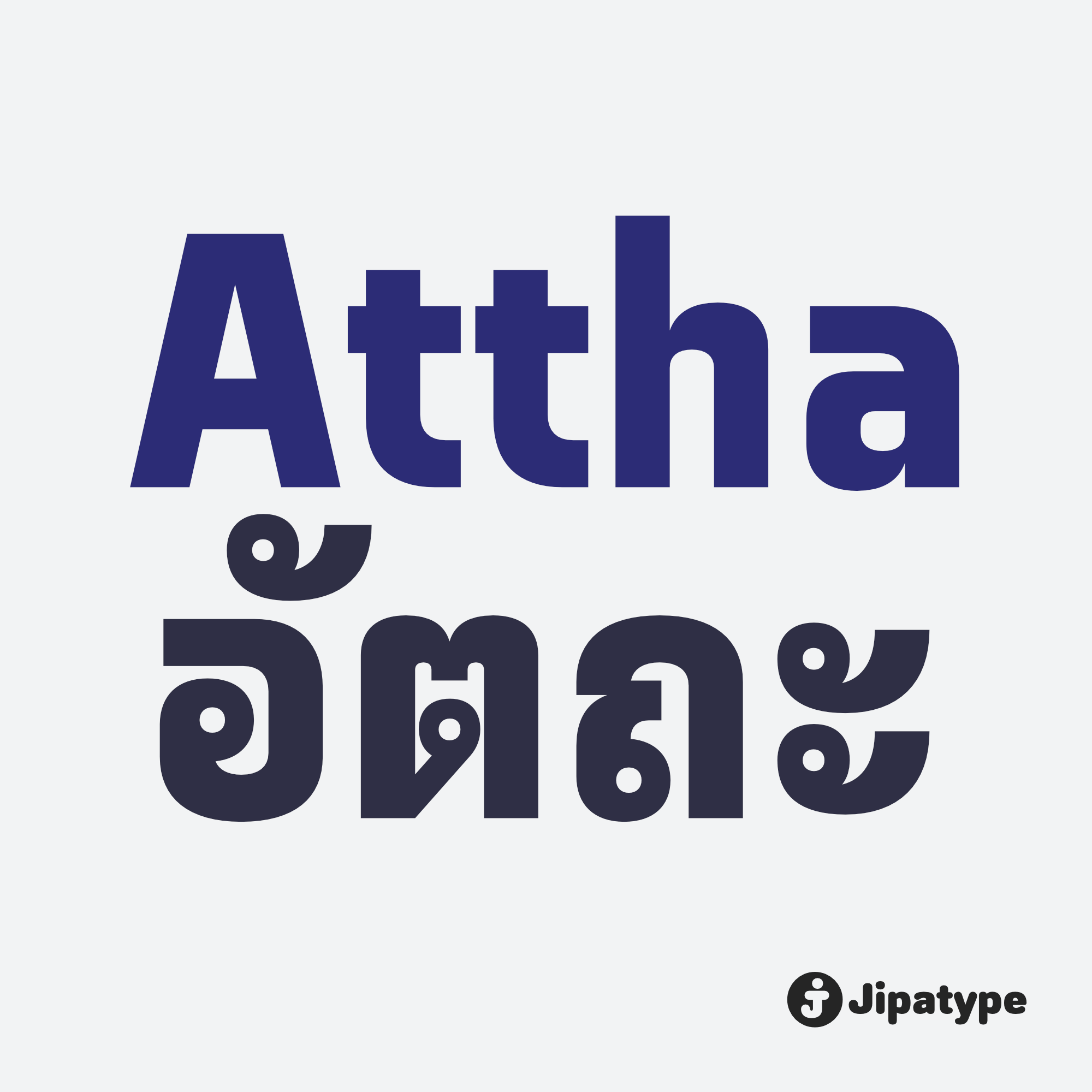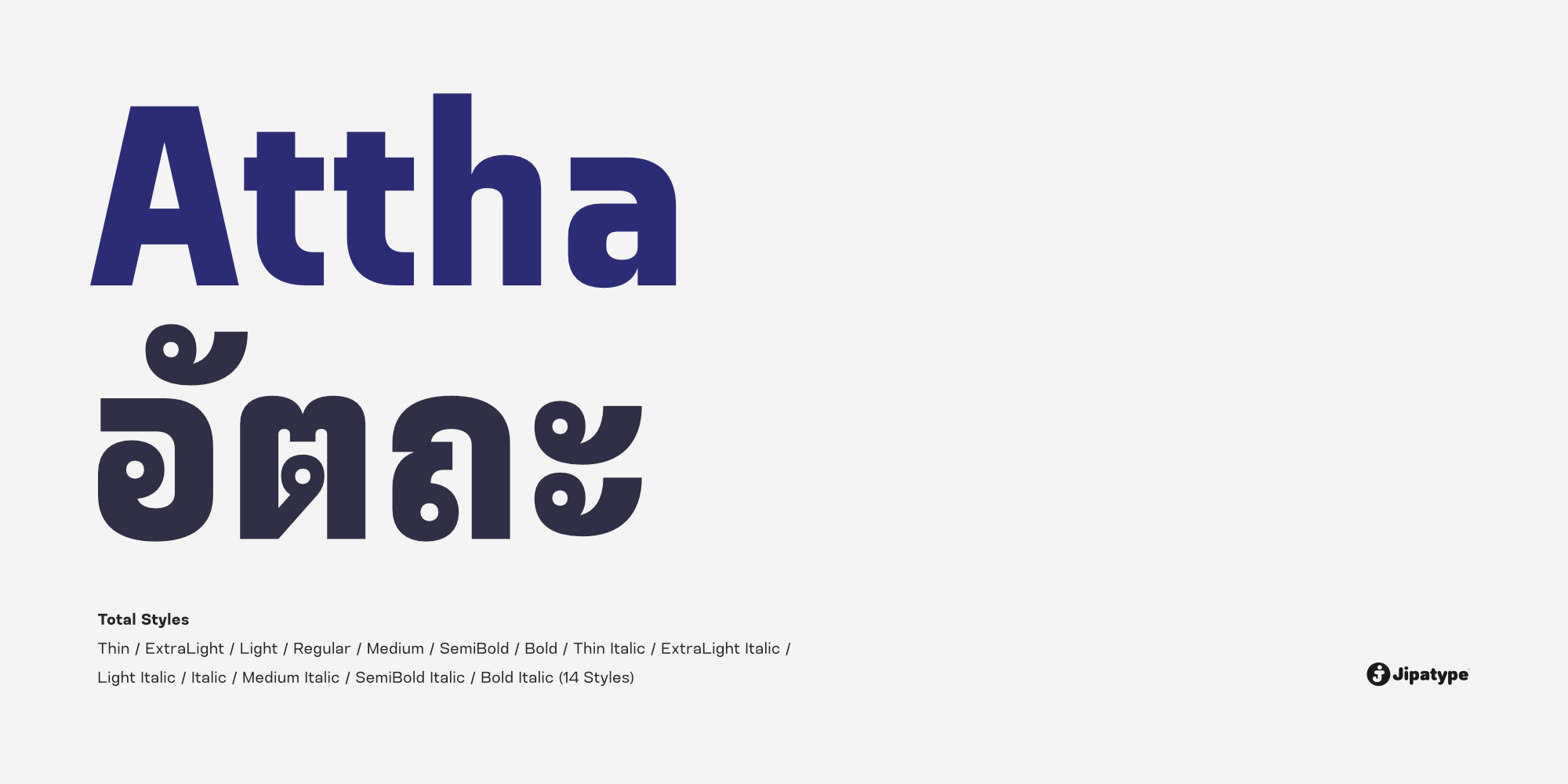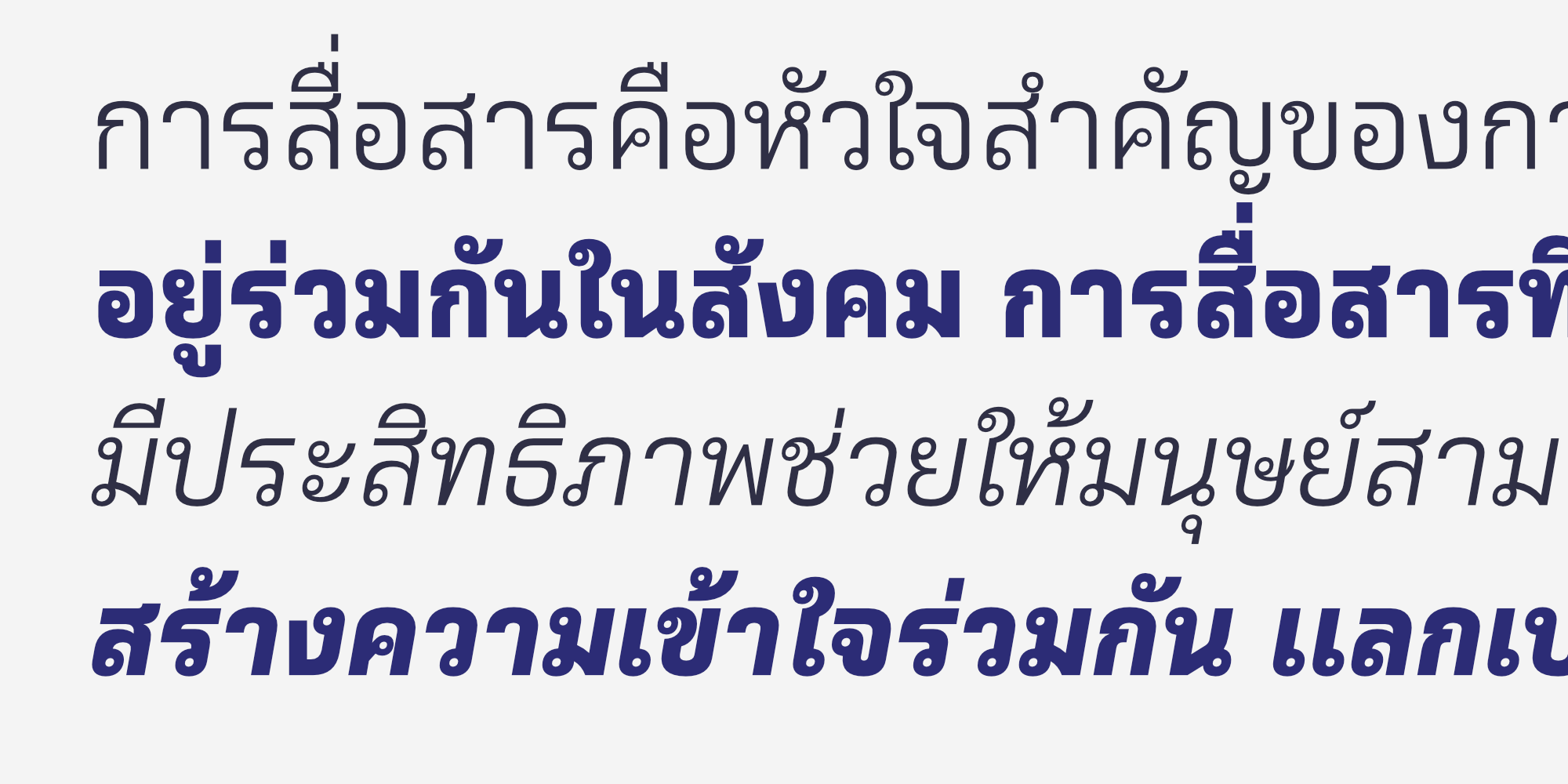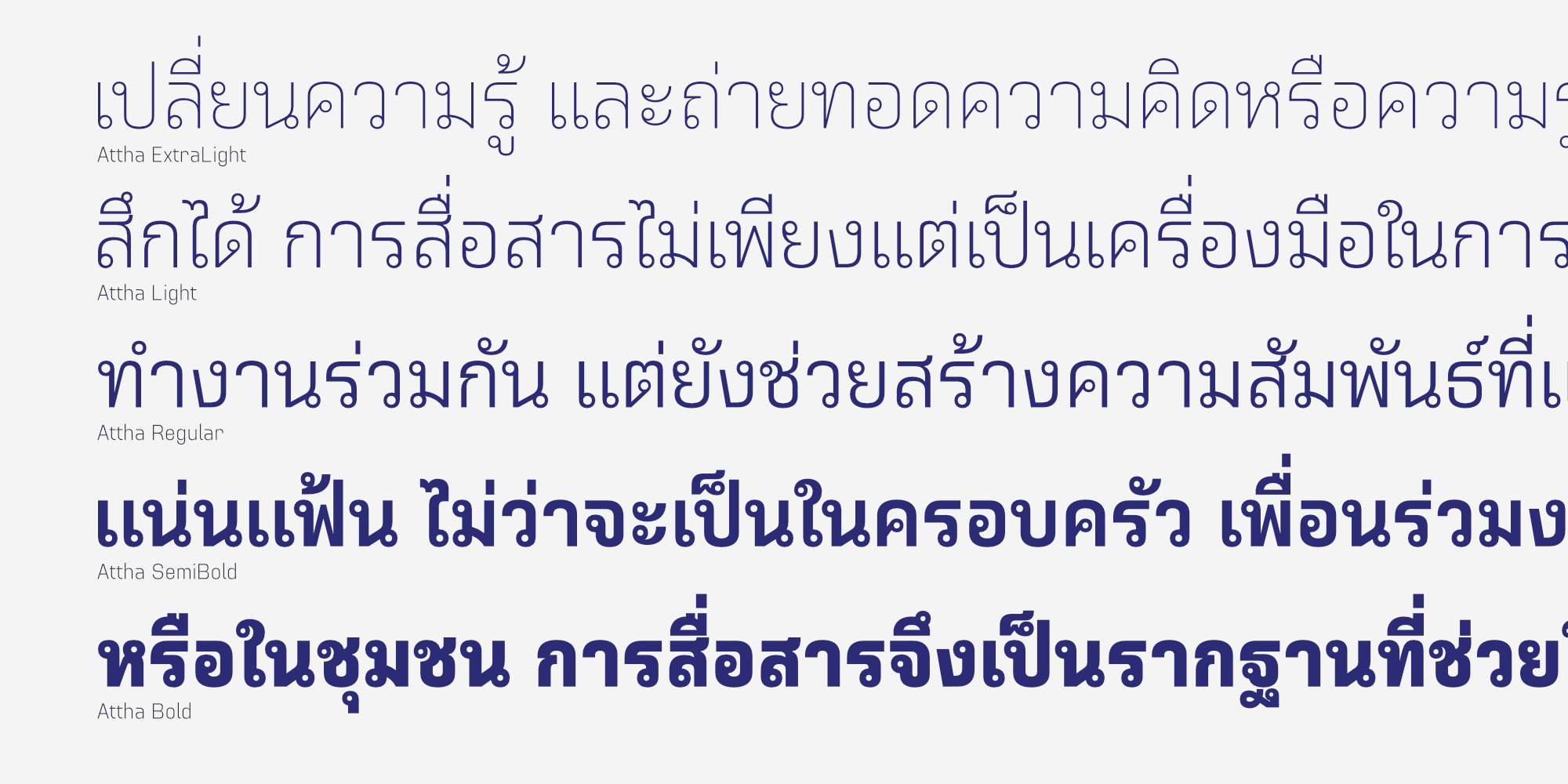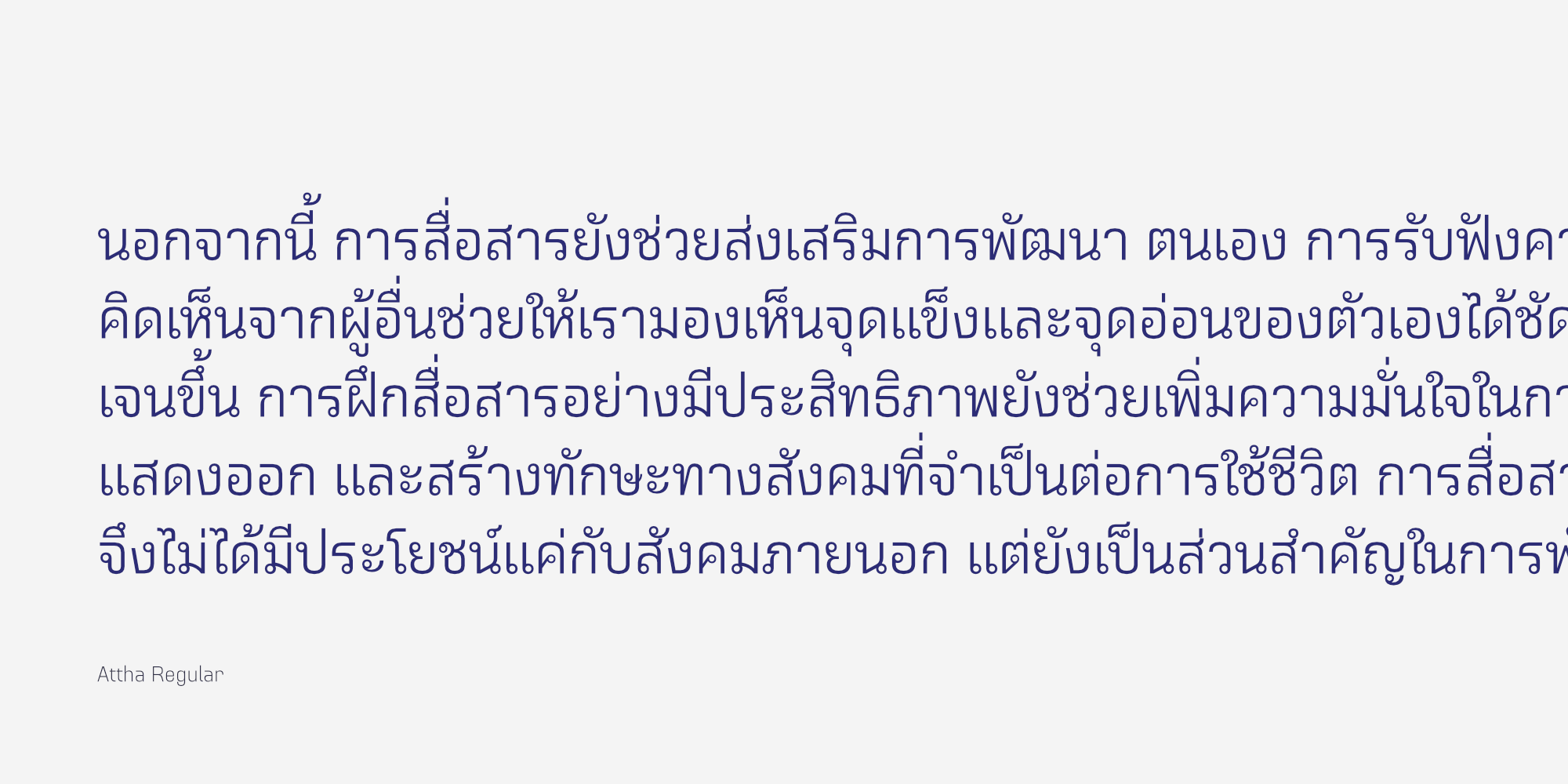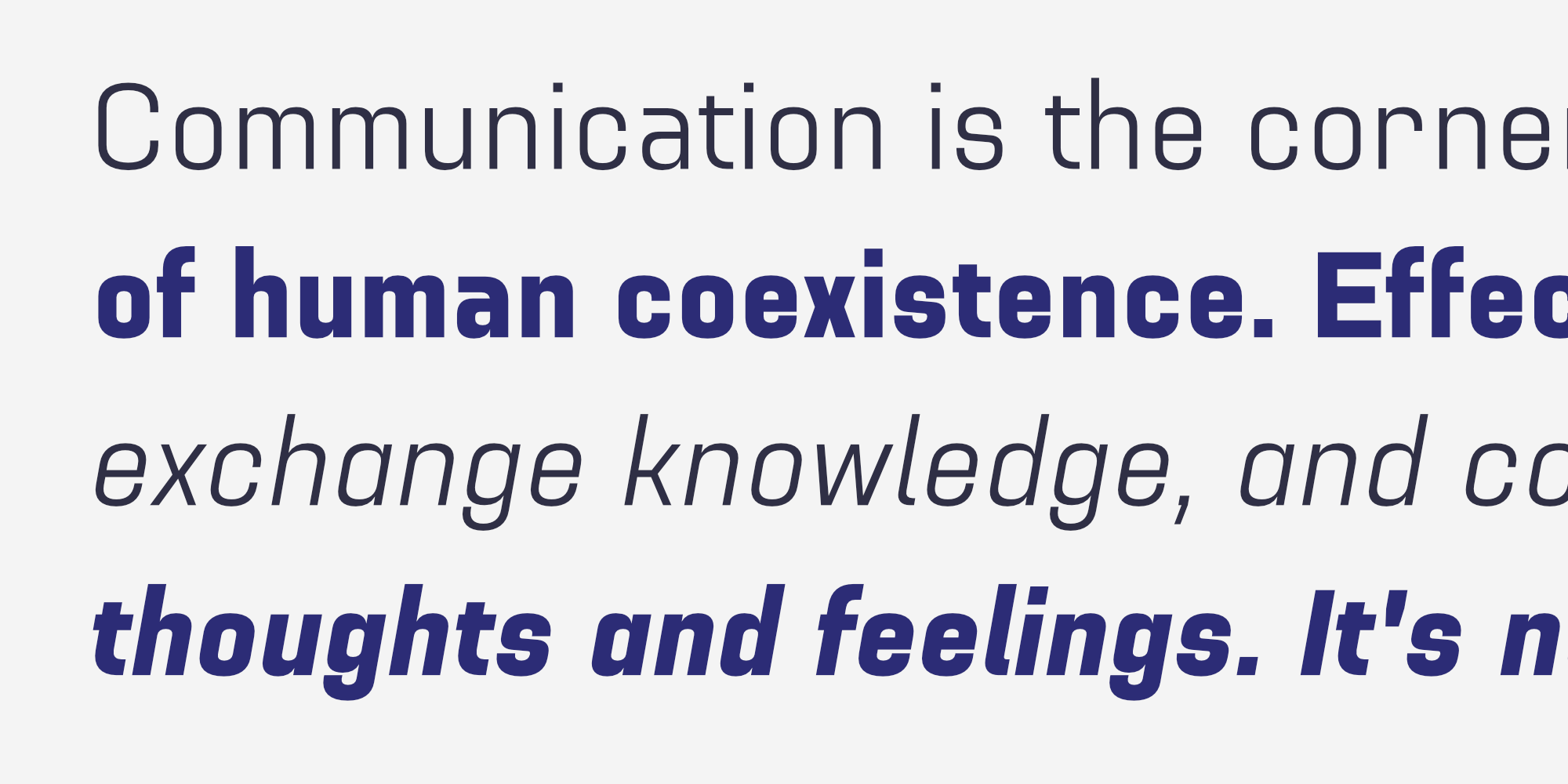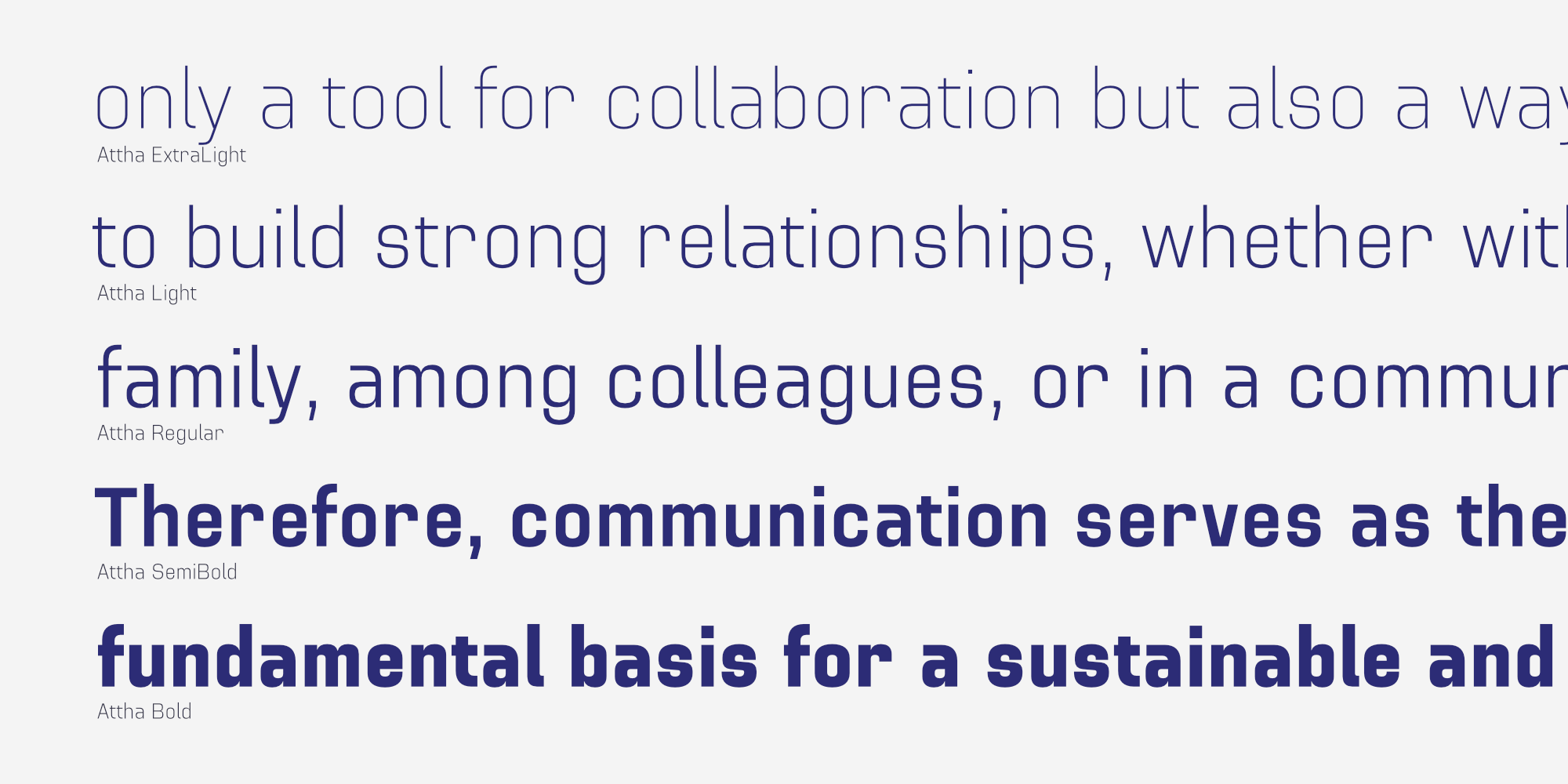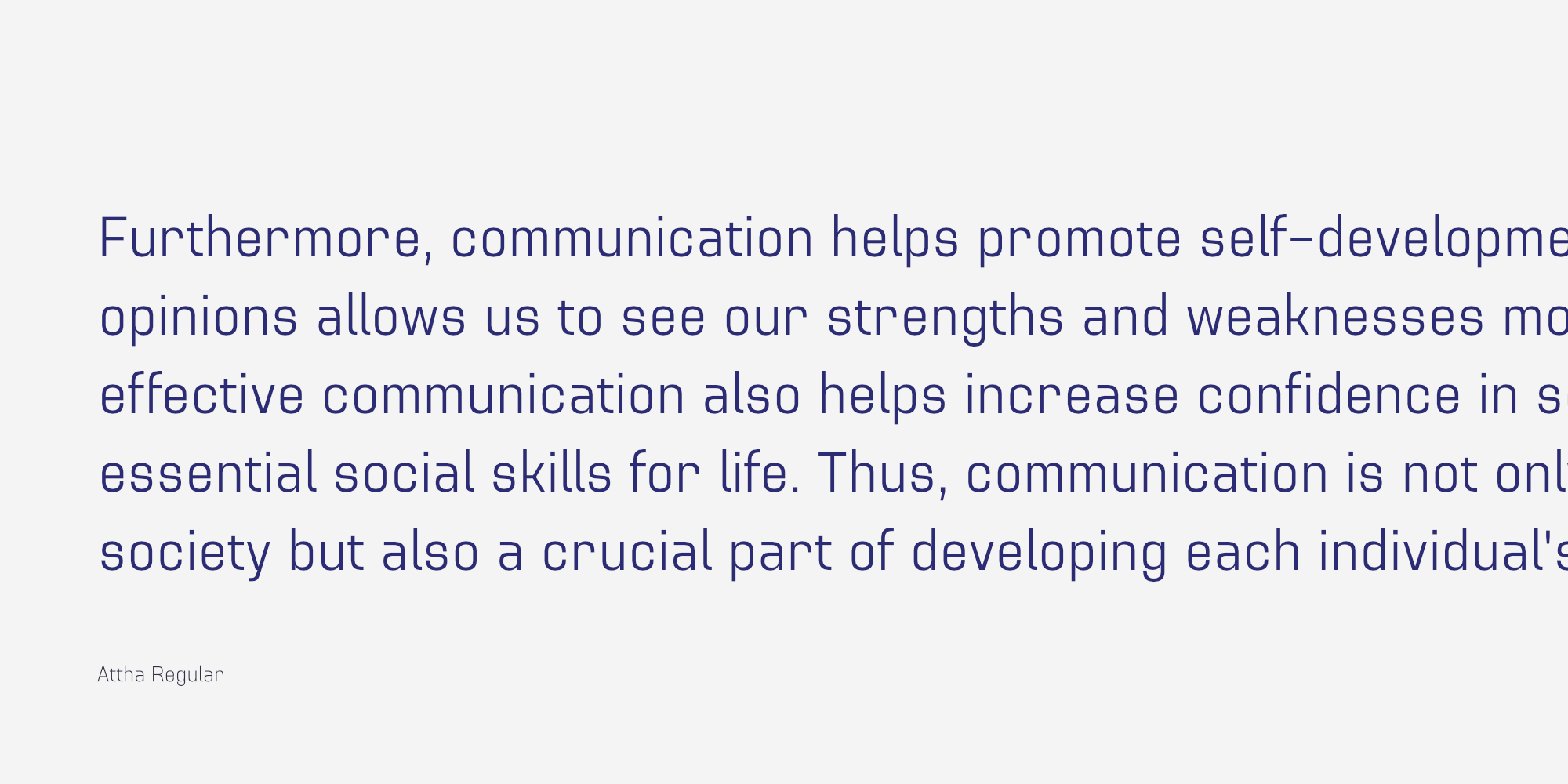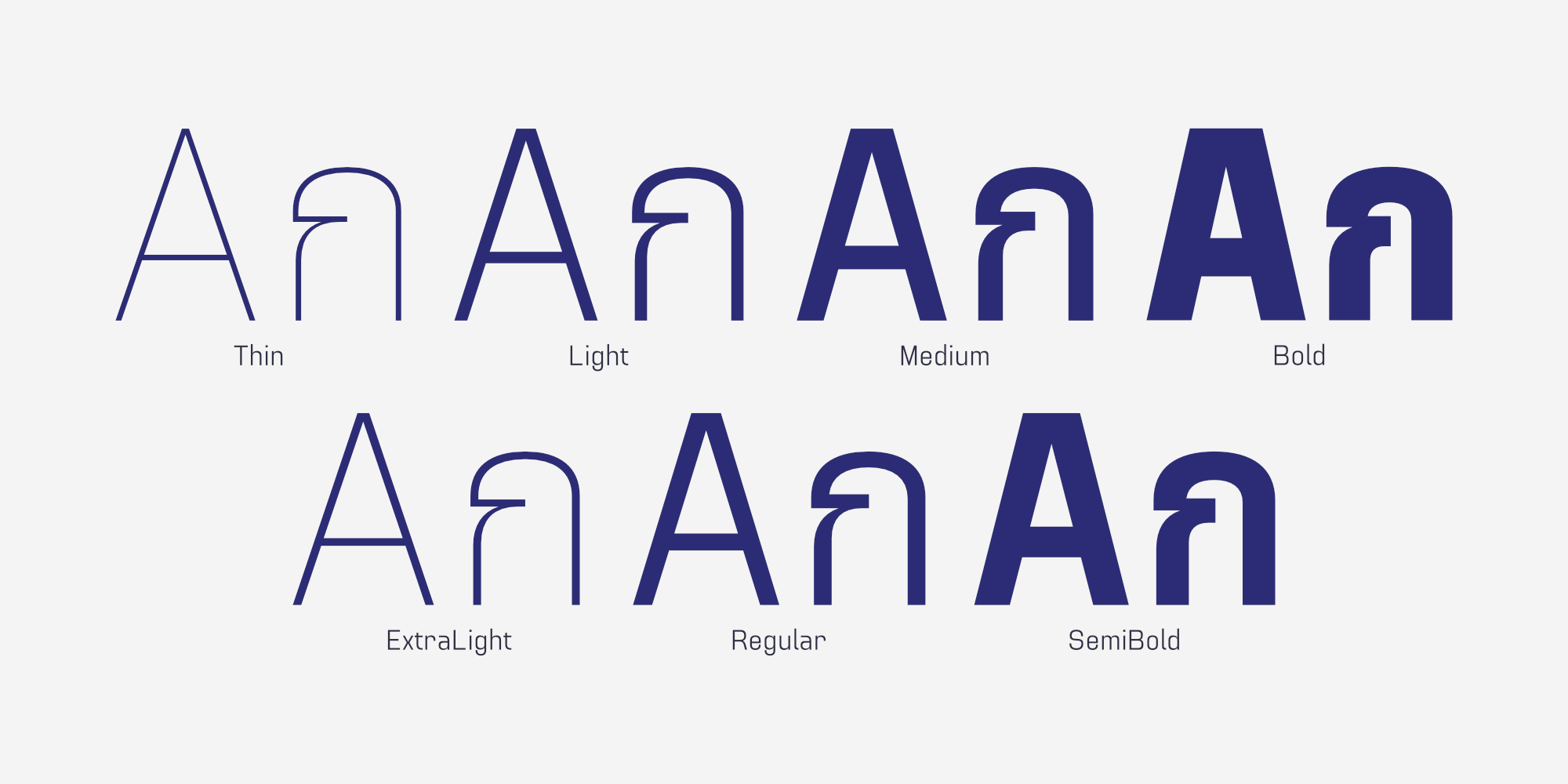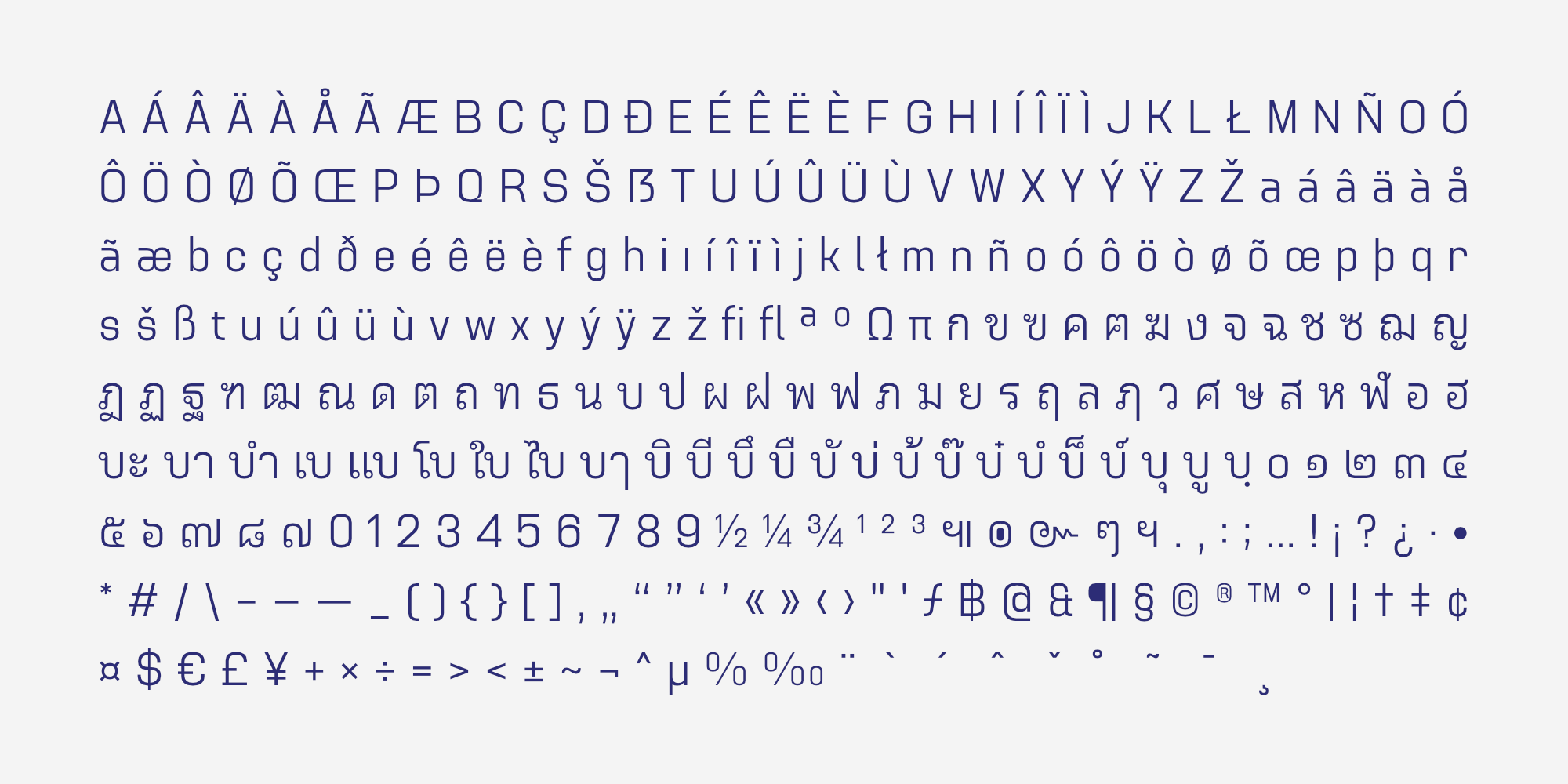
อัตถะ | Attha
Attha คือชุดตัวอักษรประเภท Sans-serif สไตล์โมเดิร์นที่เน้นโครงสร้างแบบ เรขาคณิต ที่มีความสมมาตรและความชัดเจนในการสื่อสาร โดดเด่นด้วยการออกแบบอักษรไทยแบบ “มีหัว” ซึ่งถูกปรับปรุงให้ดูร่วมสมัยและเป็นระเบียบ หัวของตัวอักษรไทยมีขนาดที่พอเหมาะและได้รับการออกแบบอย่างพิถีพิถันเพื่อรักษามาตรฐานการอ่าน
การออกแบบของ Attha มุ่งเน้นไปที่ความสะอาดตาและความคมชัด โดยมีลักษณะเด่นคือ การเก็บปลายเส้นแบบตัดตรงและคมชัดเช่น อ ล ร ซึ่งให้ความรู้สึกหนักแน่น เด็ดขาด และมีความเป็นมืออาชีพ จึงเป็นตัวเลือกที่ยอดเยี่ยมสำหรับงานที่ต้องการความน่าเชื่อถือ ความเป็นองค์กร และความทันสมัย เช่น Corporate Identity, สื่อสิ่งพิมพ์ทางธุรกิจ
ออกแบบโดย : อานุภาพ ใจชำนาญ (Anupap Jaichumnan)